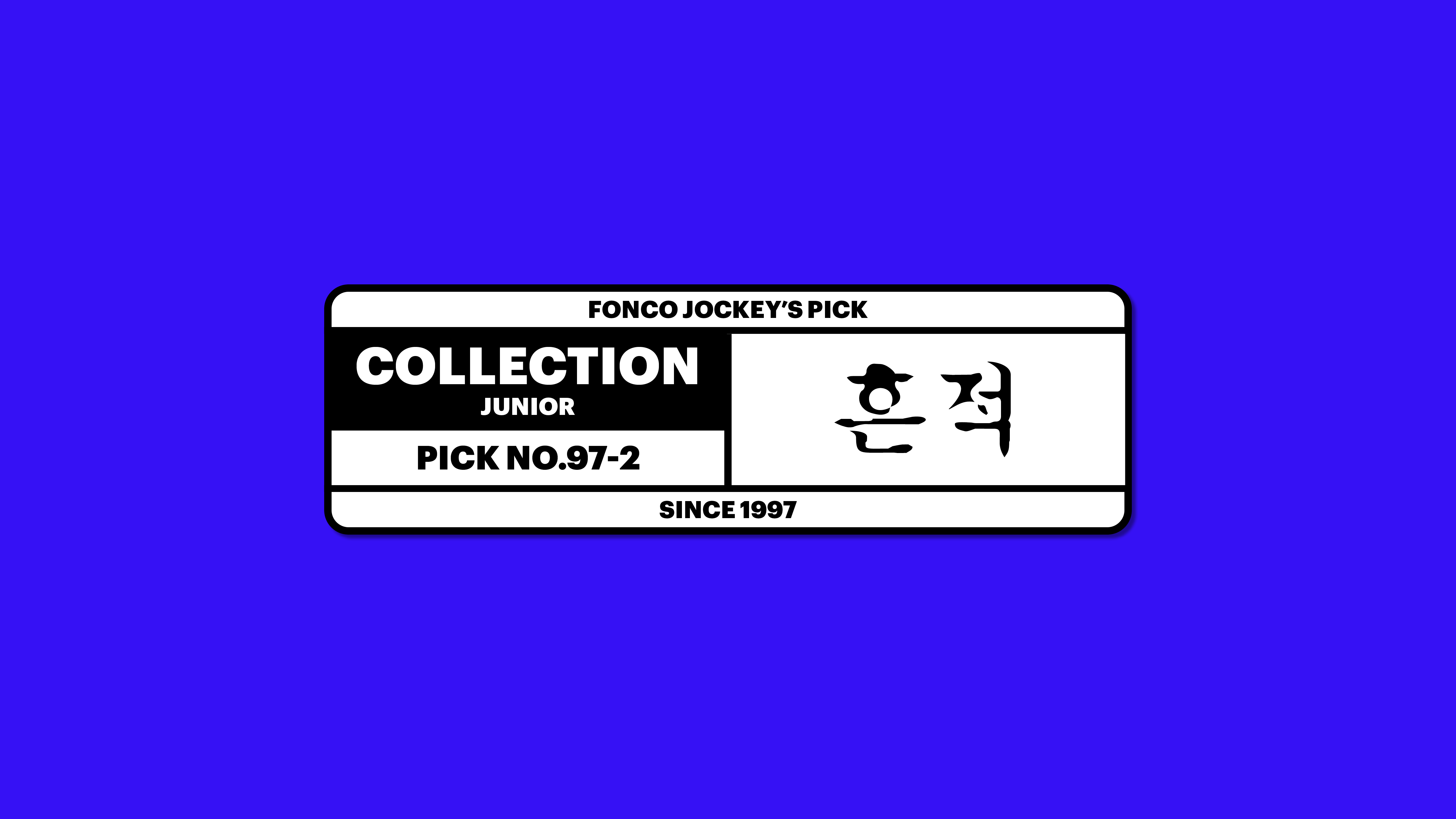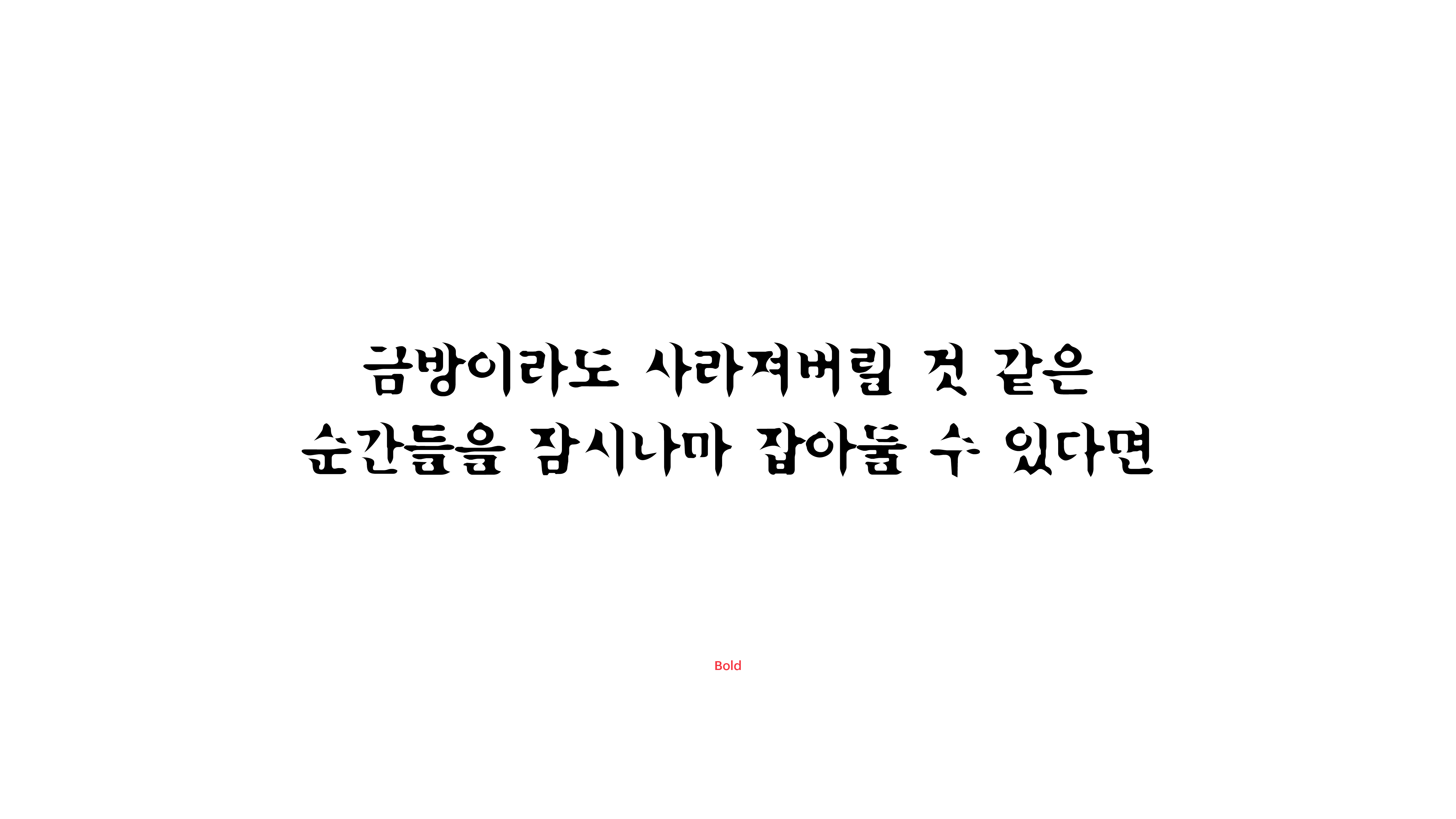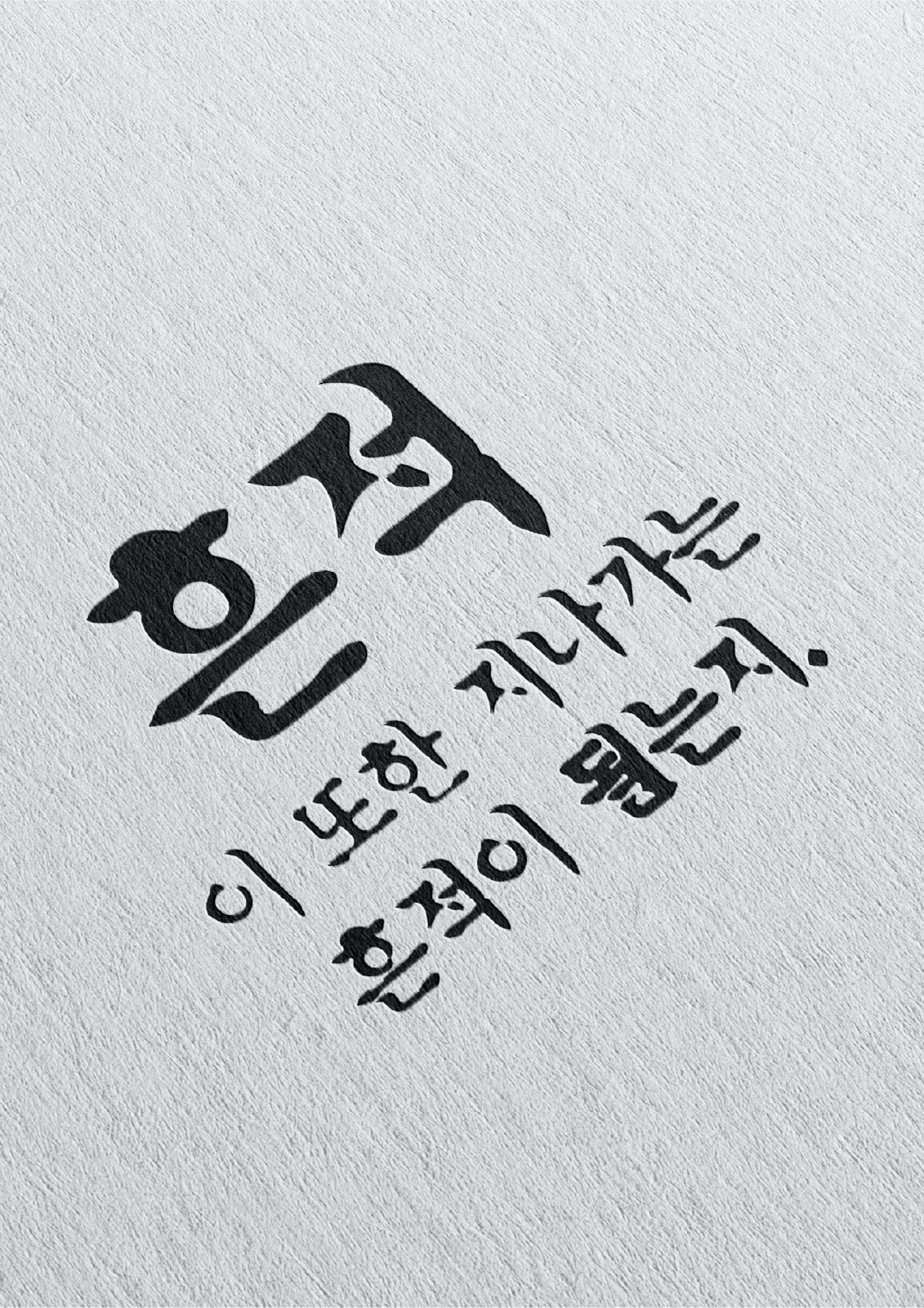
흔적
Yoon 흔적
금방이라도 사라져버릴 것 같은 순간들을 잠시나마 잡아둘 수 있다면 얼마나 좋을까요? 흔적체는 그런 순간들을 붙잡아 기록하기 위한 폰트입니다. 사라지는 부분에서 시각적 연상을 느낄 수 있도록 세심하게 디자인하여, 가독성 문제를 해결했어요. 그러니 아무 걱정 말고 소중한 감성을 가득 담아 사용해보세요.